Local brand và in áo là nhóm thiết kế rất nhạy với cá tính chữ. Một chiếc áo thun trơn có thể trở thành sản phẩm có chất riêng chỉ nhờ một headline, một logo chữ hoặc một cụm typography đủ mạnh. Ngược lại, nếu chọn font sai, áo dễ bị giống template đại trà, khó bán và thiếu nhận diện.
Bài viết này gợi ý các font TH Việt hóa trên Font S99 phù hợp cho áo thun, hoodie, streetwear, sportswear, graphic tee, áo đội nhóm, poster drop sale, lookbook và mockup local brand. Mình chủ động chọn các font TH khác nhóm bài gần đây để bộ gợi ý mới hơn, nghiêng về chất mạnh, bụi, thể thao, công nghệ, retro và đường phố.
Thiết kế in áo khác thiết kế poster thuần. Chữ không chỉ nằm trên màn hình, nó còn xuất hiện trên form áo, chất vải, ngực trái, lưng áo, tay áo, tag cổ, túi giấy và ảnh lookbook. Vì vậy, font cần đủ rõ khi in, đủ cá tính khi mặc và đủ bền khi thương hiệu dùng nhiều mùa.
Một font local brand tốt thường có ba điểm: dáng chữ có nhận diện, nét đủ chắc để in lụa hoặc in decal, và dấu tiếng Việt không phá bố cục. Các cụm như Sống khác đi, Không dành cho số đông, Local made, Áo thun form rộng, Drop mới hôm nay cần hiển thị gọn, không bị rối dấu.
Đừng chỉ xem font ở kích thước lớn. Hãy thử nó trên ngực áo nhỏ, sau lưng áo lớn, tag size, poster sale và thumbnail social. Nếu font vẫn giữ chất ở nhiều kích thước, đó mới là font đáng đưa vào hệ thống local brand.
Áo thun, hoodie và tote bag thường cần chữ có nét đủ dày. Font quá mảnh dễ mất chi tiết khi in nhỏ, in trên vải tối hoặc dùng kỹ thuật ép nhiệt.
Local brand cần nhận diện. Font quá trung tính có thể an toàn nhưng khó tạo chất. Hãy chọn font theo tinh thần thương hiệu: thể thao, bụi, retro, công nghệ, Nhật, gothic, tối giản hay rebellious.
Nhiều local brand dùng slogan tiếng Việt. Font TH Việt hóa giúp dấu rõ hơn, giảm lỗi khi in những câu ngắn có dấu như Chậm mà chất, Tự do mặc, Đừng hòa tan.
Font mạnh nên dùng cho logo, headline, graphic lớn. Font phụ nên dùng cho size chart, giá, mô tả chất liệu, thông tin sản phẩm và CTA.
Nếu local brand đi theo hướng áo thể thao, áo bóng đá, jersey, racing, gymwear hoặc teamwear, font cần có lực. Dáng chữ nên chắc, hơi góc cạnh, dễ nhìn từ xa và hợp khi đặt số áo, tên đội, slogan hoặc logo lớn sau lưng.
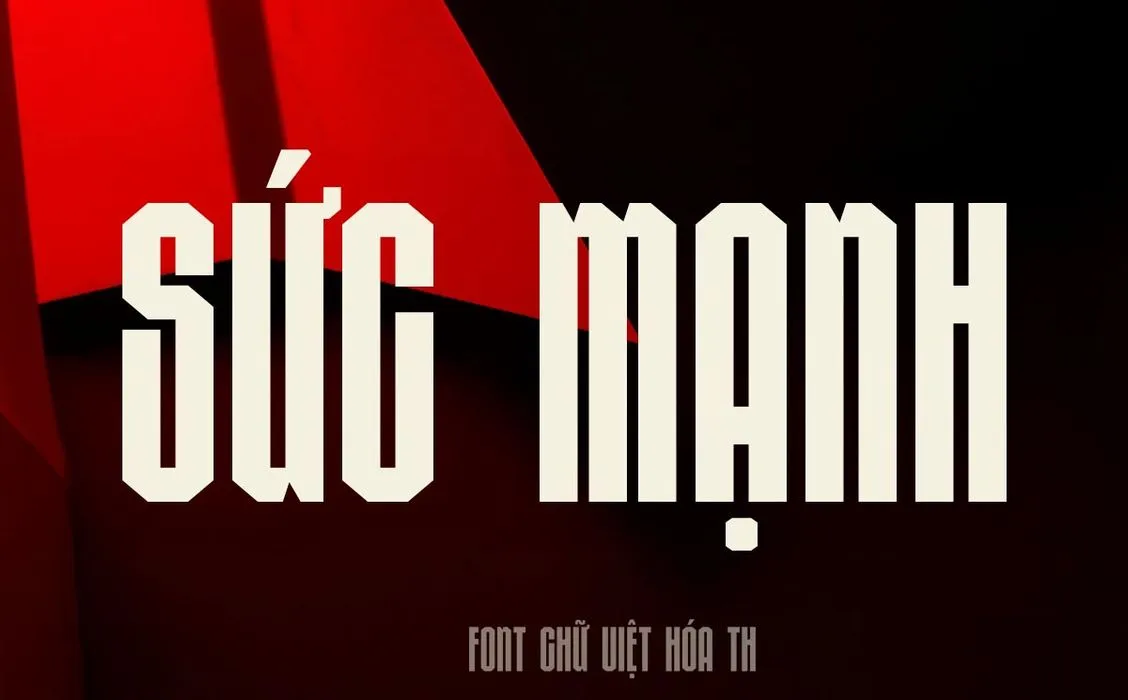
Nhóm font này hợp với áo team building, áo thể thao local, áo chạy bộ, áo bóng rổ, áo đá bóng, áo gym và poster drop thể thao. Khi dùng, hãy thử chữ trên nền đen, trắng, đỏ, xanh navy và neon để xem độ tương phản.
Với số áo hoặc tên đội, nên dùng chữ in hoa ngắn. Với slogan dài, hãy giảm tracking và chia dòng rõ. Font thể thao đẹp nhất khi nó có khoảng thở và không bị ép quá nhiều chữ trong một mảng in nhỏ.
Streetwear và graphic tee cần font có năng lượng mạnh hơn. Chữ có thể góc cạnh, lạ, hơi game, hơi underground hoặc mang cảm giác văn hóa đường phố. Đây là nhóm phù hợp cho áo oversize, hoodie, poster lookbook, sticker pack và social drop mới.
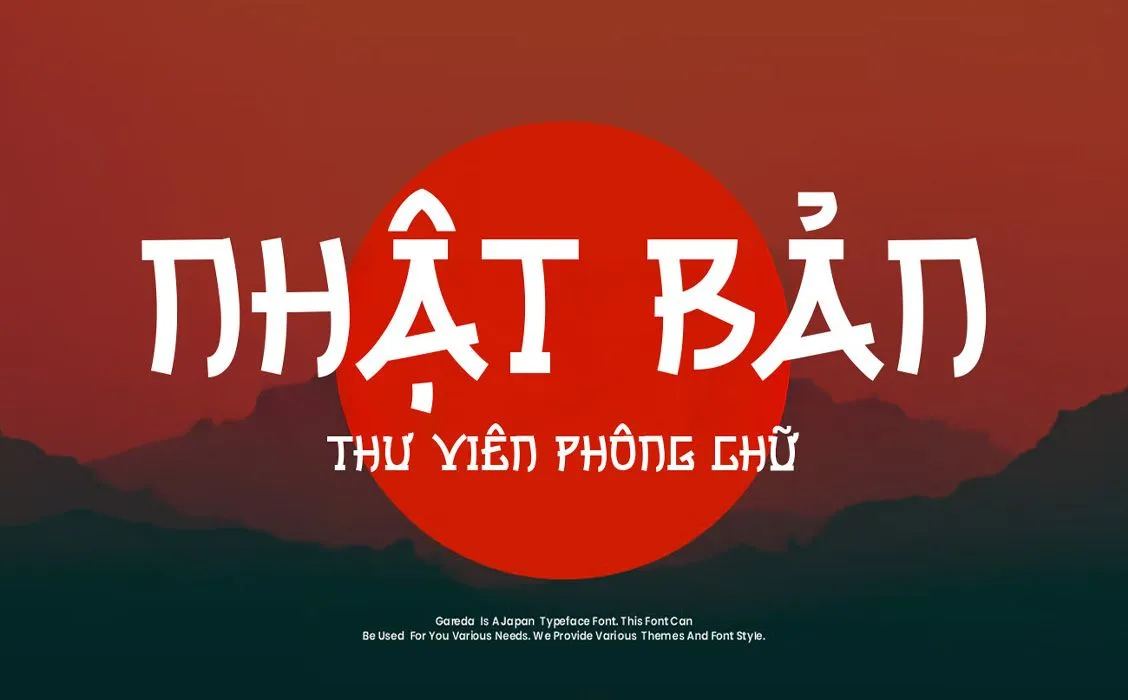
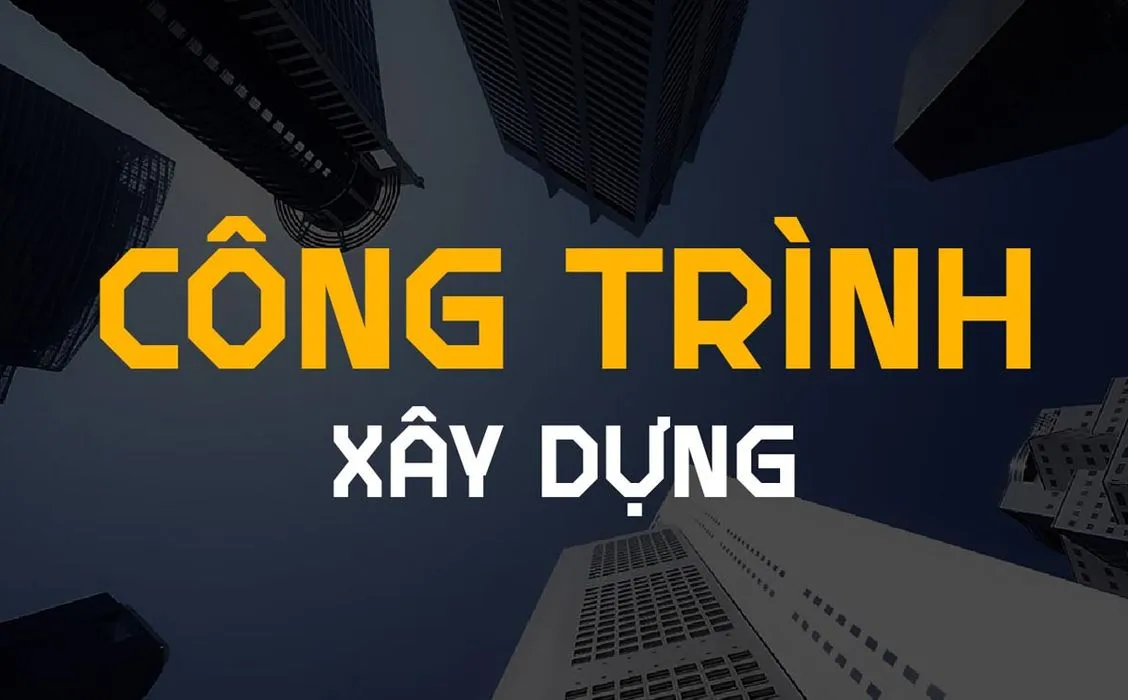
Nhóm này hợp với các câu ngắn như Out of line, Không theo khuôn, Made for noise, Drop 01, Street unit, Local never dies. Với thiết kế in lưng áo, bạn có thể dùng font display lớn và phối thêm icon, texture hoặc hình minh họa.
Một lưu ý nhỏ: font streetwear thường rất có cá tính, nên đừng dùng quá nhiều font cùng lúc. Một font chính đủ mạnh, một font phụ đơn giản và một bố cục tốt sẽ tạo cảm giác chuyên nghiệp hơn.
Một số local brand không đi theo hướng bụi mà theo chất future, techwear, minimal, cyber, monochrome hoặc unisex. Lúc này font công nghệ, mono hoặc sans display sẽ hợp hơn font retro hay thể thao.
Font TH Axiome - Tải về
Font TH Degrad Mono - Tải về
Font TH AQUXE - Tải về
Nhóm này hợp với áo techwear, áo đen trắng, jacket, hoodie oversize, lookbook studio, landing page drop sale và poster dạng grid. Hãy phối với màu đen, xám, bạc, xanh điện, xanh neon hoặc nền ảnh công nghiệp để tạo chất hiện đại.
Với techwear, chữ nên sạch và có hệ thống. Đừng dùng hiệu ứng quá nhiều. Chỉ cần font có dáng lạ, bố cục căn lưới tốt và khoảng trắng đủ mạnh là thiết kế đã có chất.
Retro và vintage là hướng rất hợp với áo thun, tote bag, áo du lịch, áo quán cafe, áo workshop, áo sự kiện và local brand có tinh thần hoài niệm. Nhóm font này tạo cảm giác thủ công, bụi, cũ vừa đủ và dễ phối với illustration.
Font TH Acttime - Tải về
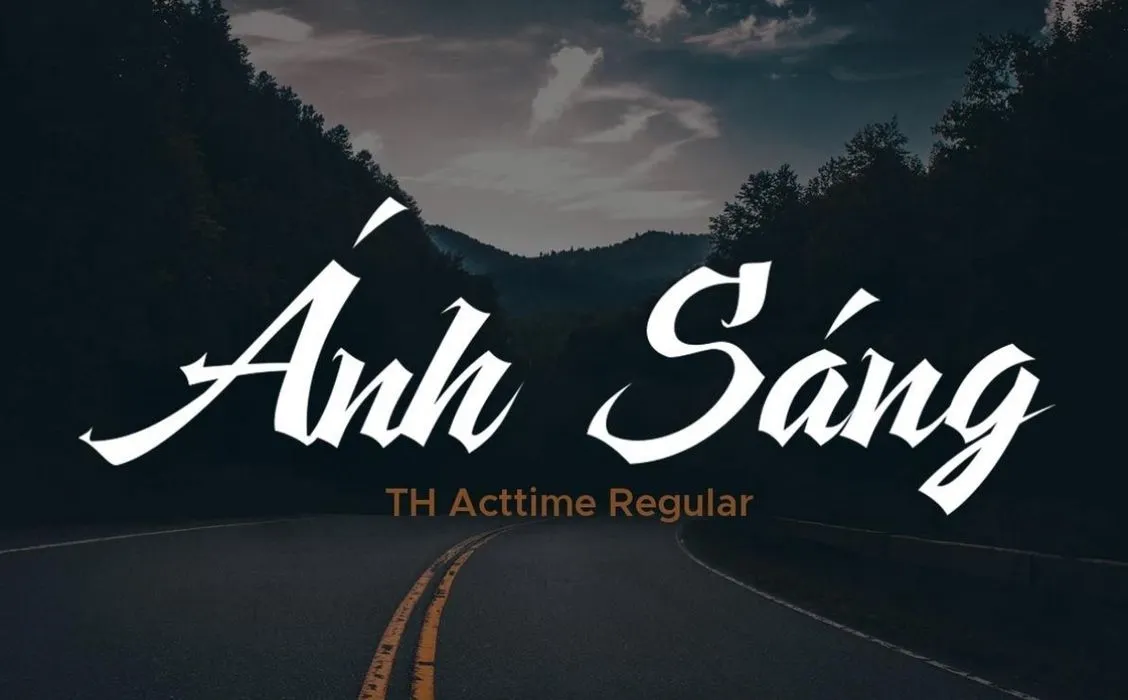
Font TH Bladfour - Tải về
Font TH Holywest - Tải về
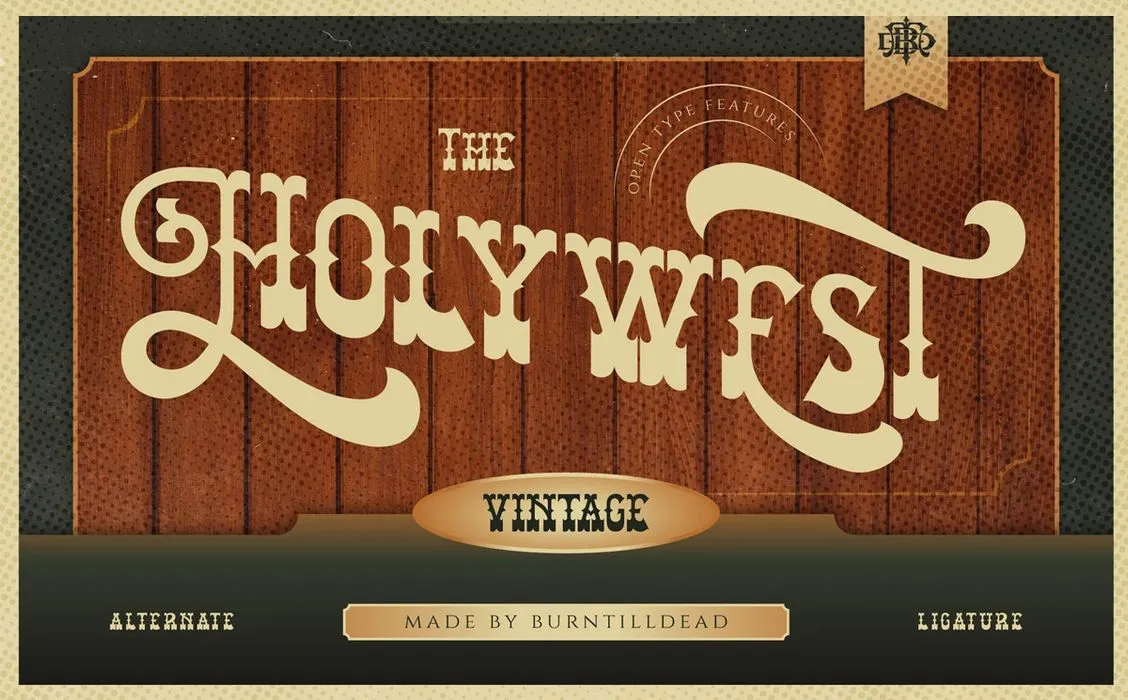
Nhóm retro nên dùng cho logo chữ, slogan, badge tròn, thiết kế in ngực trái, graphic sau lưng hoặc tem nhãn. Nếu thiết kế có nhiều texture, hãy giữ chữ đủ to để không bị mất nét khi in.
Font chữ local brand, in áo cần có cá tính nhưng vẫn phải sản xuất được. Hãy chọn font TH mạnh cho áo thể thao, font display cho streetwear, font công nghệ cho techwear, font retro cho vintage tee và luôn kiểm tra chữ trên mockup áo thật trước khi in.